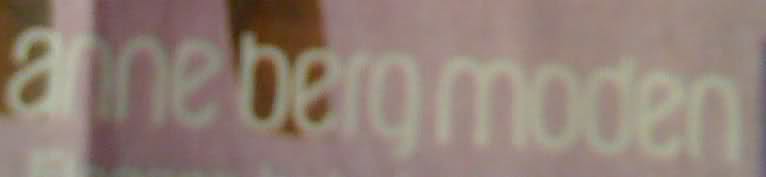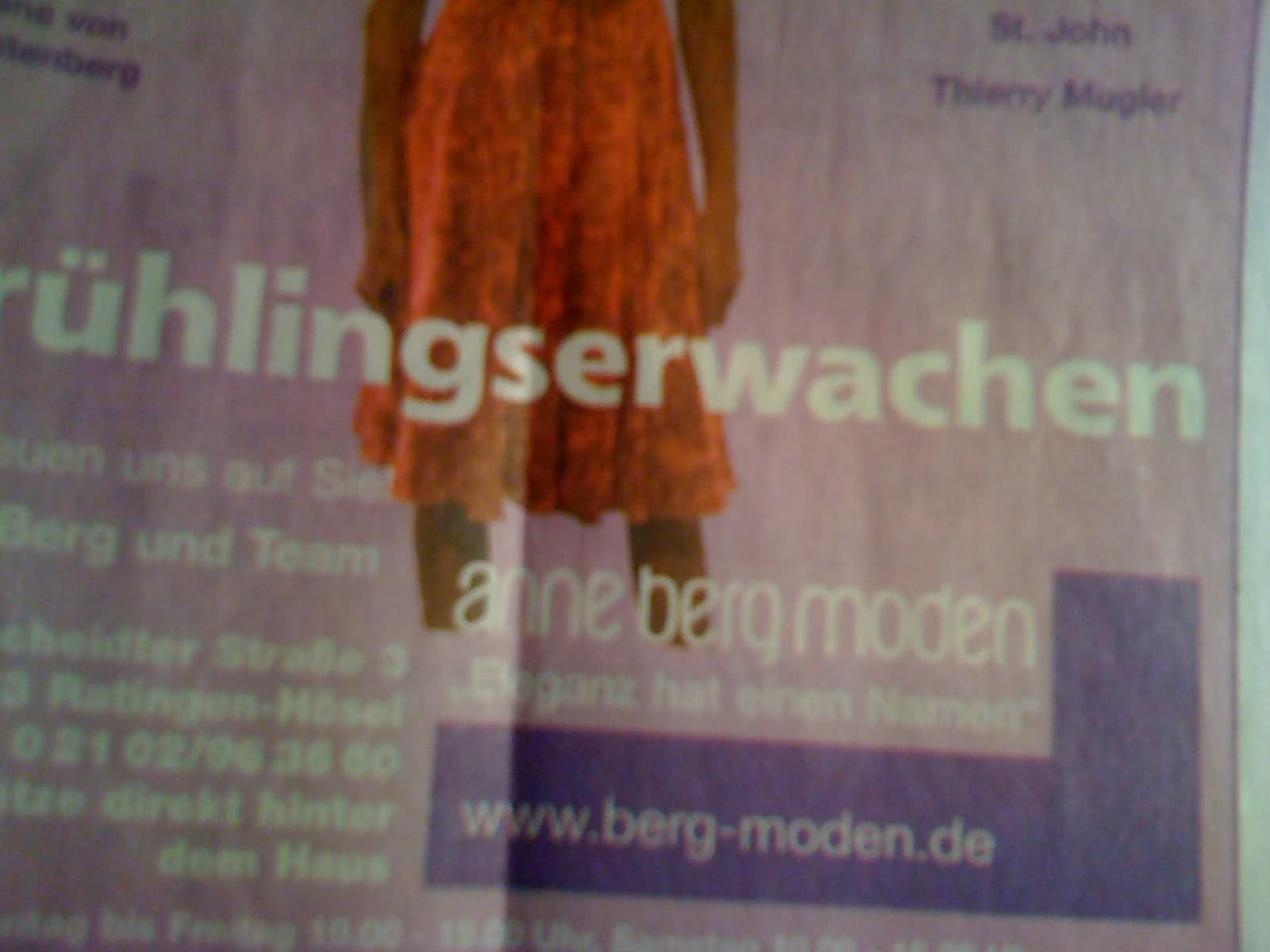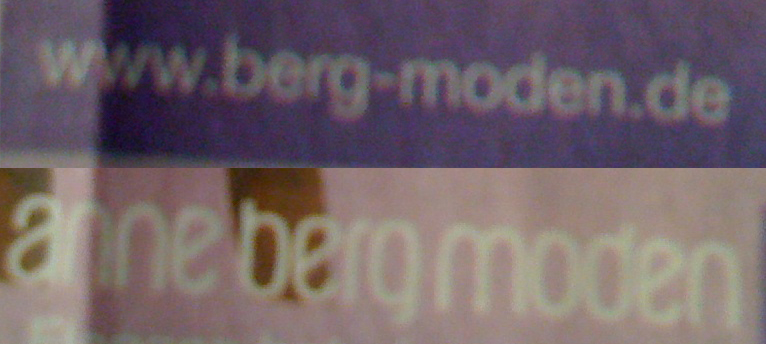
Kennt jemand diese Grotesk?
könnte die DejaVu Sans sein …
es geht um die Webadresse:
Ich hatte den Bildausschnitt falsch gewählt.
Kann man überhaupt etwas erkennen?
örks, das ist natürlich schwer zu sagen, das Bild ist einfach zu schlecht. Es könnte aber aus der DejaVu die Condensed sein … aber die Betonung liegt auf „könnte“. Wenn die Überschrift aus der Familie gesetzt ist, warum nicht auch der Rest?
Eh.. nein. Es ist dieselbe Vorlage.
Kennzeichnend: Der Schrägstrich im Gemeinen e und die sehr kurzen senkrechten bei den Gemeinen b, d etc.
Du hast diese zwei Vorlagen gepostet:
Das sind nun mal verschiedene Schriften.
(Während ich noch Bilder gebastelt hab, hat Ralf das textlich gelöst :D )
Stimmt. Tut mir leid wegen der Konfusion.
Gemeint ist die Schrift mit den flachen Oberlängen der Gemeinen und dem Schrägstrich im Gemeinen e.
Gibt's nicht einen Freefont namens advent, der in dieser Art gehalten ist?
Ich denke auch, dass advent da ran kommt?!